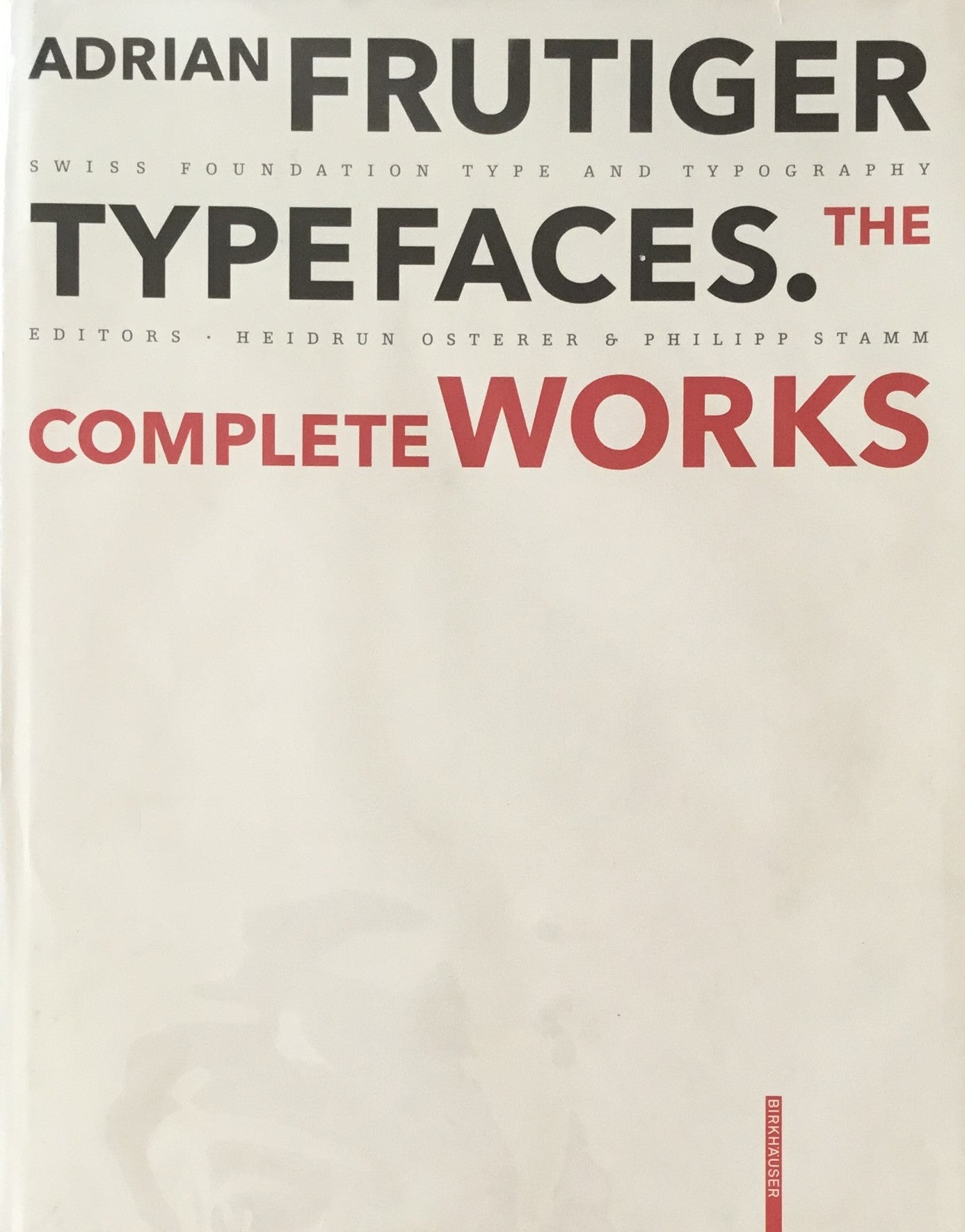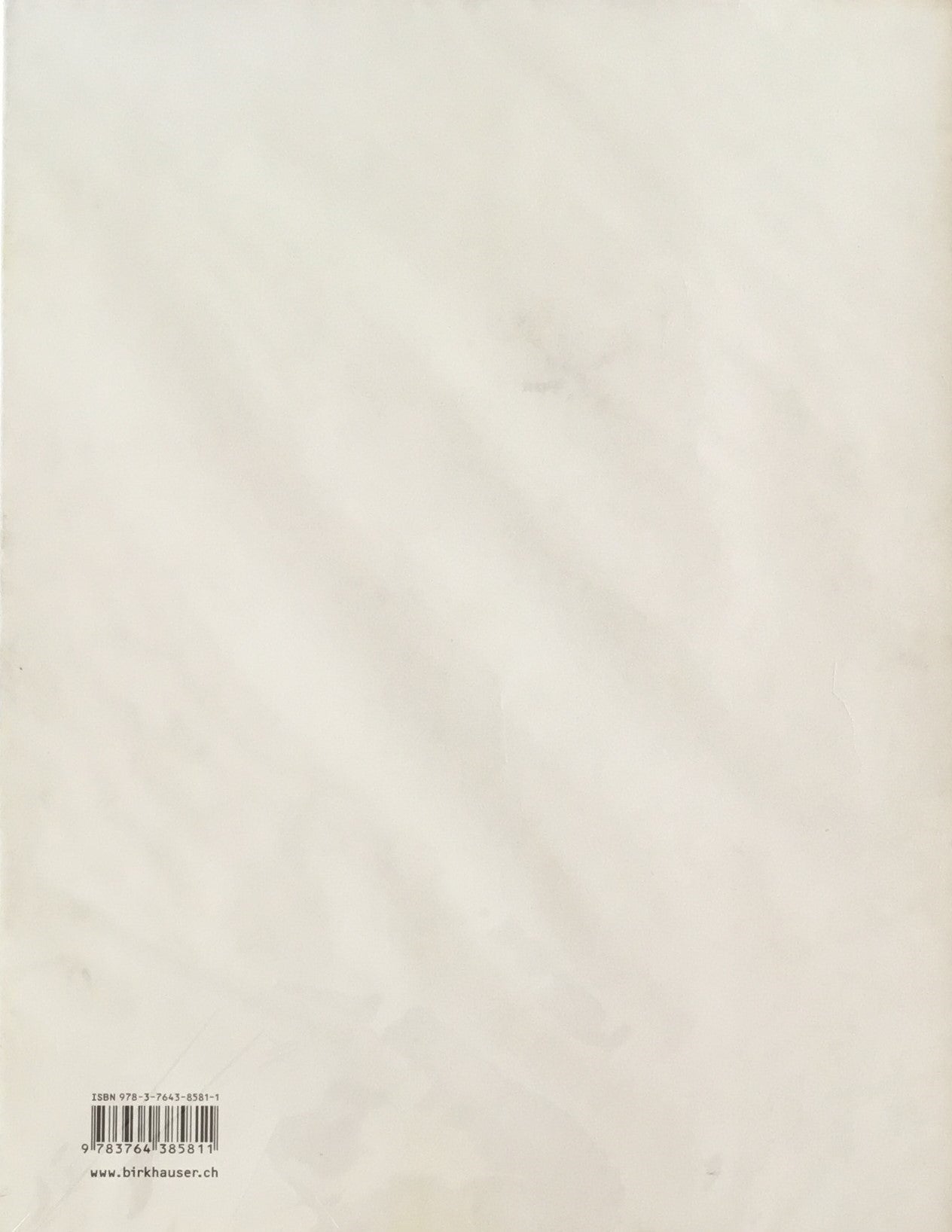
Adrian Frutiger Typefaces The Complete Works アドリアン・フルティガー タイポフェイス
2009 Birkhäuser Architecture Heidrun Osterer/ Philipp Stamm ハードカバー 大型本
本の内容 スイスの書体デザイナー。フランスの シャルル・ドゴール空港の サインに使われる フルティガーというフォントで有名。その仕事のすべてを 写真や 制作資料などでみせる コンプリートブック。